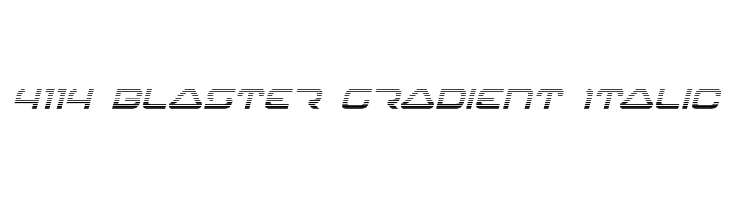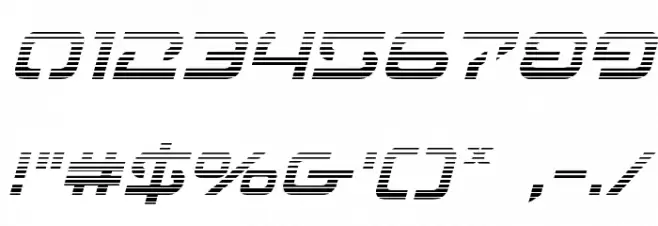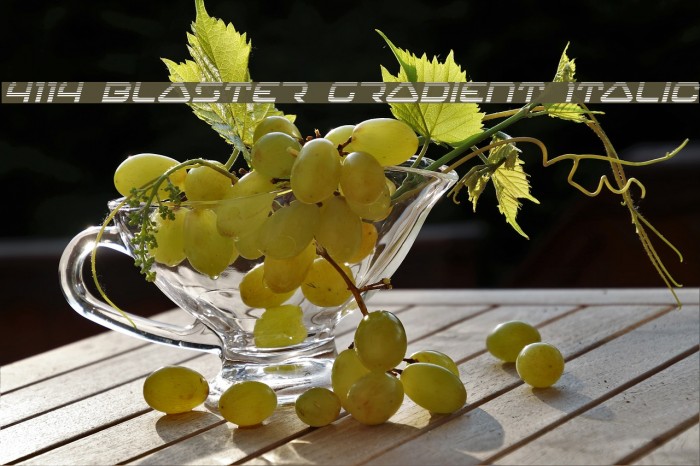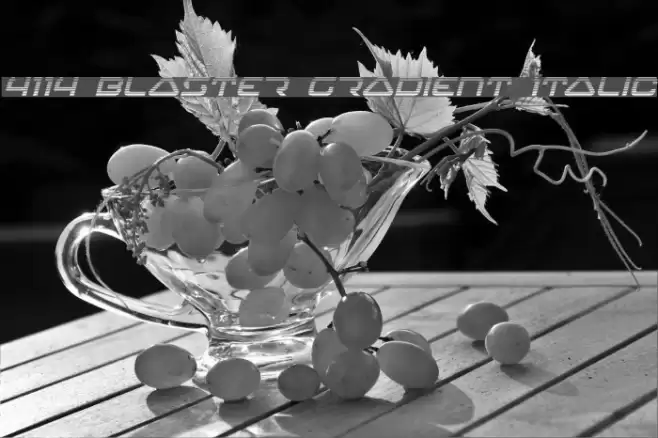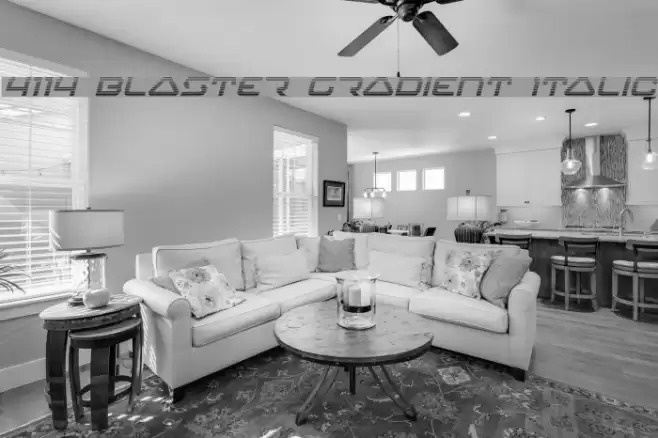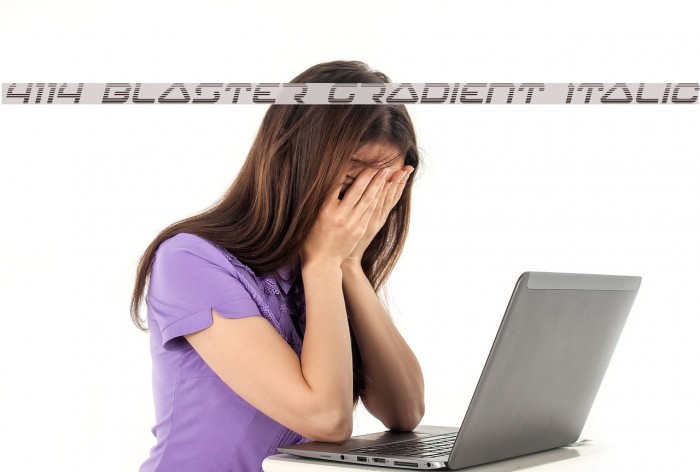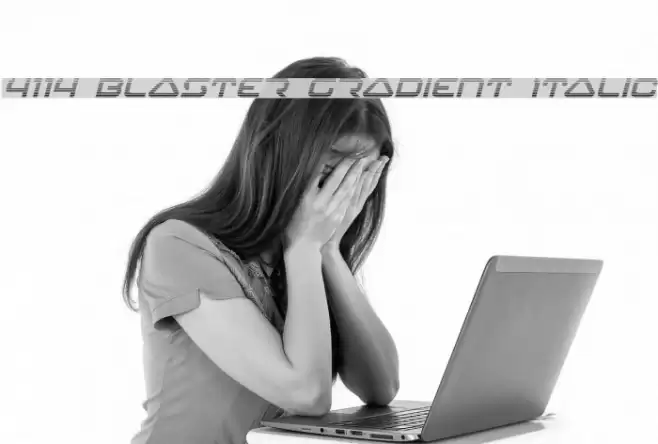
4114 Blaster Gradient Italic Font
| इटैलिक | Yes |
| उपयोग का मामला | Headlines, Logos, Posters |
| सुझाए गए प्रोजेक्ट | Ideal for sci-fi themed designs, video game graphics, tech branding, and modern posters. |